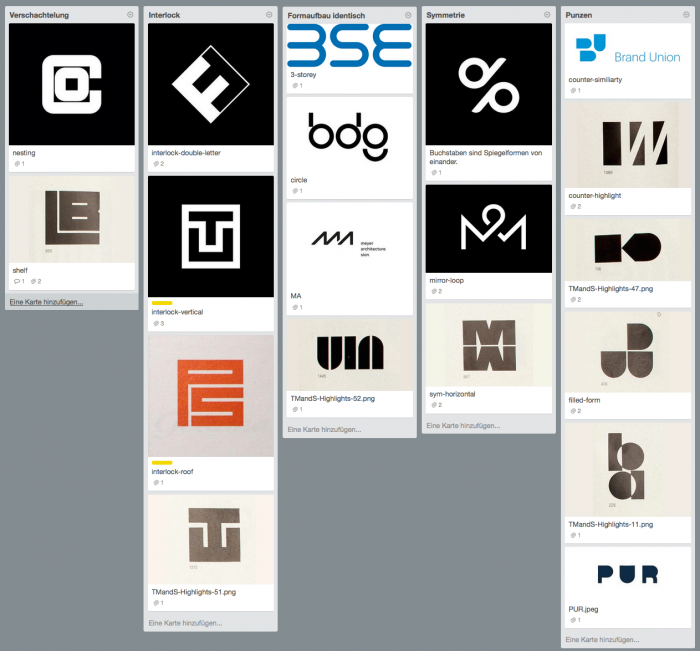
Logozeichen Kategorisierung
ich bin gerade dabei Typo-Logos nach ihren Design-Prinzipien zu kategorisieren.
Was ihr in dem angehängten Bild seht, ist so ein grober Ausschnitt was ich schon gesammelt habe.
Bislang habe ich einfach Bücher und Pinterest-Sammlungen durchforstet und meine Fundstücke gesammelt.
Nach einer gewissen Zeit hat man dann soviel Material, dass sich Logoideen dann irgendwann wiederholen und man
kann anfangen, Schubladen/Kategorien zu entwerfen.
Jetzt meine Frage: Kennt ihr Logo-Bücher, die Logos auf diese Art und Weise sammeln? Wäre natürlich super bequem für mich, dann müsste ich weniger Zeit in eine passende Terminologie stecken. Bücher/Seiten, die meine Sammlung erweitern, sind natürlich ebenso willkommen.
Ich wollte diese Frage auch noch in einem englischsprachigen Forum posten. Ich habe „Typography + Forum“ gegoogelt und siehe da, Ralf's typography.guru ist bereits auf Platz 1 im Google-Ranking. Glückwunsch ;)
Bei deinen Beispielen wundert mich, dass du LB und PS in verschiedene Kategorien gepackt hast. BSE, UIN, FF(mit Einschränkung) sind auch punktsymmetrisch, TU und TW achsensymmetrisch.
Ich denke, dass du ein Logo nicht genau einer Kategorie zuordnen kannst, sondern eher mehren Prinzipien. Auf TU passt sowohl Interlock als auch Achsensymmetrie (vertikale Achse) zu. TW wäre für mich eher Verbunden als Interlock. Bei mirror-loop spielt neben der Symmetrie die Überschneidung eine Rolle. Bei ba gibt es wieder eine andere Art der Überlappung.
Spannendes Thema, eine Buchempfehlung kann ich leider nicht beisteuern.
Die Bücher von Michael Evamy beinhalten eine nachvollziehbare Logo-Kategorisierung. Darüber hinaus könntest du dir auch das aktuelle Buch ›Logo Modernism‹ aus dem Taschen-Verlag anschauen.
Ich habe Logo Modernism nun vor mir liegen. Nun stellt sich für mich wie bei jedem Logobuch die Frage: Woher haben die all die Logos in hochauflösender Form? Werden die zum Teil nachgebastelt?
Normalerweise würde ich denken, dass jedes Logo beim Urheber, beziehungsweise dem entsprechenden Nutzungsrechteinhaber angefragt und die Verwendung abgeklärt wird. Bei Büchern wie der Logo Lounge werden die Logos von den Urhebern auf der Website eingereicht (man muss sich dort registrieren und eine Jahresgebühr zahlen) und dann entscheidet die Jury, sobald die thematischen Kategorien für die neue Ausgabe feststehen, welche Entwürfe es ins Buch schaffen. Ist die Auswahl getroffen, fordert die Jury die Druckdaten bei den Urhebern an.
Ja, das ist deutlich einfacher und klarer, aber bei der ›Logo Modernism‹ hast du tausende von Logos. Ich kann mir nicht vorstellen, dass man bei jedem Logo die Nutzungsrechte eingeholt hat. Viele Unternehmen zu den Logos gibt es auch nicht mehr und man kann die Logos auch kaum ergoogeln, man findet nur verpixelte Ergebnisse.
Nun, ich könnte mir gut vorstellen, dass viele der Logos z.B. von hier kommen:
Hier stecken eben auch alte Logos, teils originale, teils auch nachbauten. Zudem ist auch Wikipedia einwe Logo-Quelle, oft eben auch den alten der Unternehmen, über die dort berichtet wird.
Trifft nicht wirklich zu. Ich habe hier gerade ein dickes Logobuch von mir liegen und 90% lassen sich nicht finden. Das Logo-Buch wurde vor ein paar Jahren veröffentlicht.
Seitdem es Logos gibt, gibt es auch Bücher, die sie zusammentragen. Das ist dann vor allem eine Frage der Recherche. Vieles wird also hochauflösend gescannt; einiges wird nachgebaut.
Müssten hier nicht rein theoretisch auch Nutzungsrechte vereinbart werden? Spätestens dann stünde ja auch einem Austausch der Reinzeichnung nichts mehr im Wege.
Ich weiß nicht, wie das mit Logos aus der Pre-Digitalisierungsära gehandhabt wird. Ich glaube aber, dass man wesentlich schneller ist, wenn man die Logos nachzeichnet bzw. hochauflösend aus vorhandenen Quellen scannt.
ich hatte auch den Autor kontaktiert und eine Antwort bekommen.
Die Logos sind aus unzähligen historischen Magazinen und Büchern und sind dann mit 1200 dpi eingescannt worden. Größere Abbildungen wurden vektorisiert/nachgezeichnet.
Im Rahmen einer redaktionellen Verwendung benötigen Logos in der Regel keine Abdruckgenehmigung.